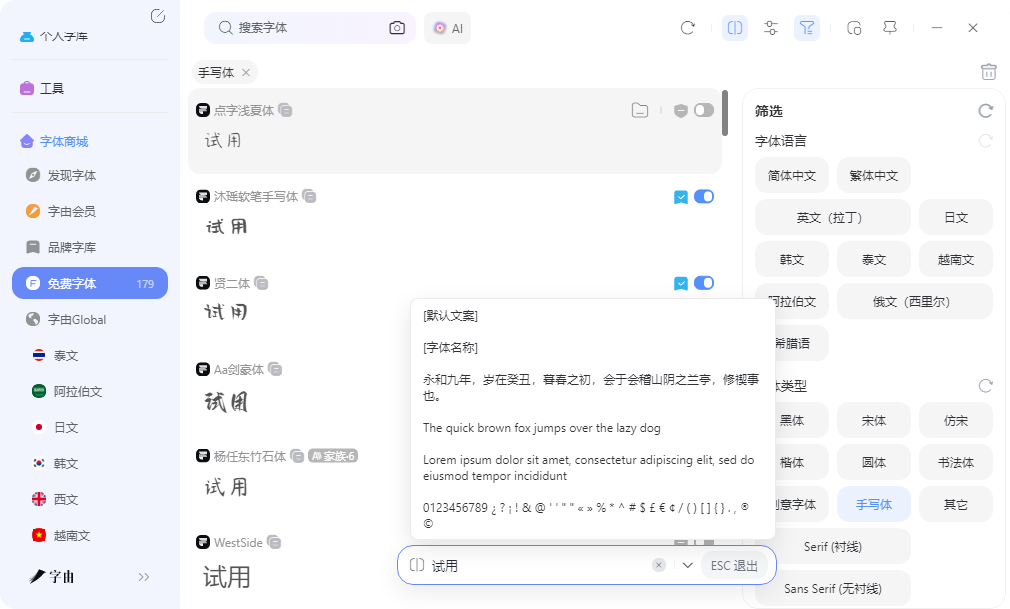
生成自己的手写字体,把你的笔迹变成电脑字体
把自己的笔迹变成电脑里能用的字体,或者在文档里打出一段像手写的文字,这两种需求都有对应的在线工具可以解决。有的工具通过上传手写稿照片生成字体文件,有的把普通文字渲染成手写风格图片。这篇文章测试了5款工具,操作难度和输出格式不同,总有一款适合你。
字由的字体库中设有手写体分类。用户打开字由客户端后,找到筛选栏的字体类型中勾选手写体,系统会列出所有手写风格的字体。这些字体包括演示悠然小楷、点字手写漆书、字由芳华体等,总计数十款。每款字体都标注了免费商用标签,用户可以放心用于商业项目。
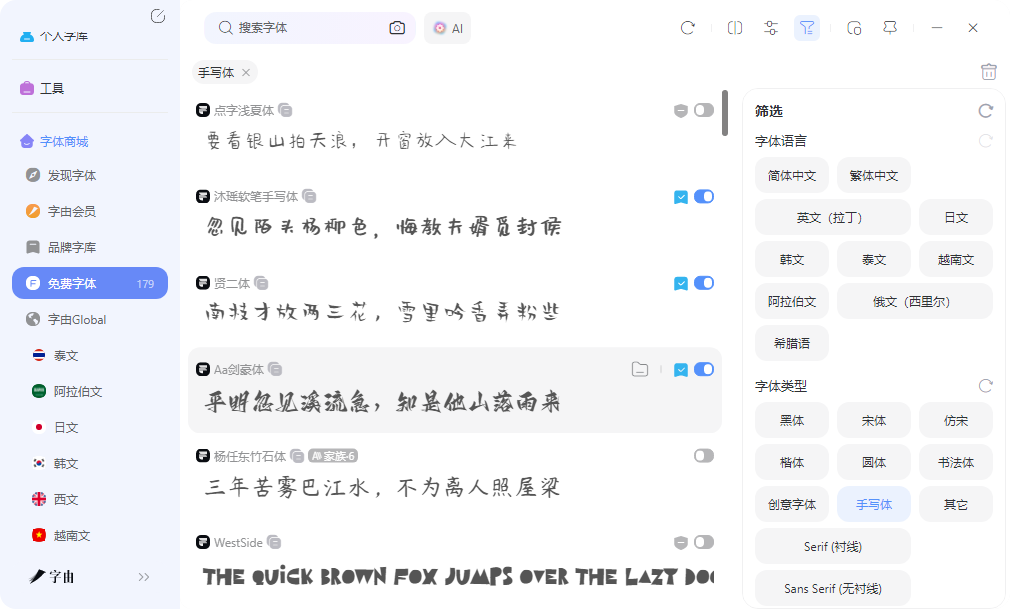
筛选手写体后,用户可以在预览区输入自己的文案,例如一段签名或一句 slogan,页面会实时显示该字体应用到文案上的效果。这个预览功能不需要激活字体,用户可以先对比多款手写体的笔画特征和整体气质。
2、handtext
第二个工具是handtext。它主要将用户输入的文本转换成看起来像手写的页面,适合生成手写版作业、笔记或信件。用户可以在编辑器中粘贴或打字输入文字,也可以上传PDF文件。页面右侧提供了多种设置选项,包括纸张类型(如A4)、方向(纵向或横向)、字体选择(支持多种手写字体)。设置完成后点击Generate按钮,系统生成手写风格的输出。输出结果可以直接打印,也可以导出为PDF。
该工具的操作界面简洁,不需要注册即可使用。生成的页面看起来像是用笔在纸上写出来的,包括字迹的深浅变化和不规则的排列。对于需要提交手写版作业的学生,或想给信件增加手写效果的用户,这个工具可以节省大量时间。免费版可能有字数限制,日常使用足够。
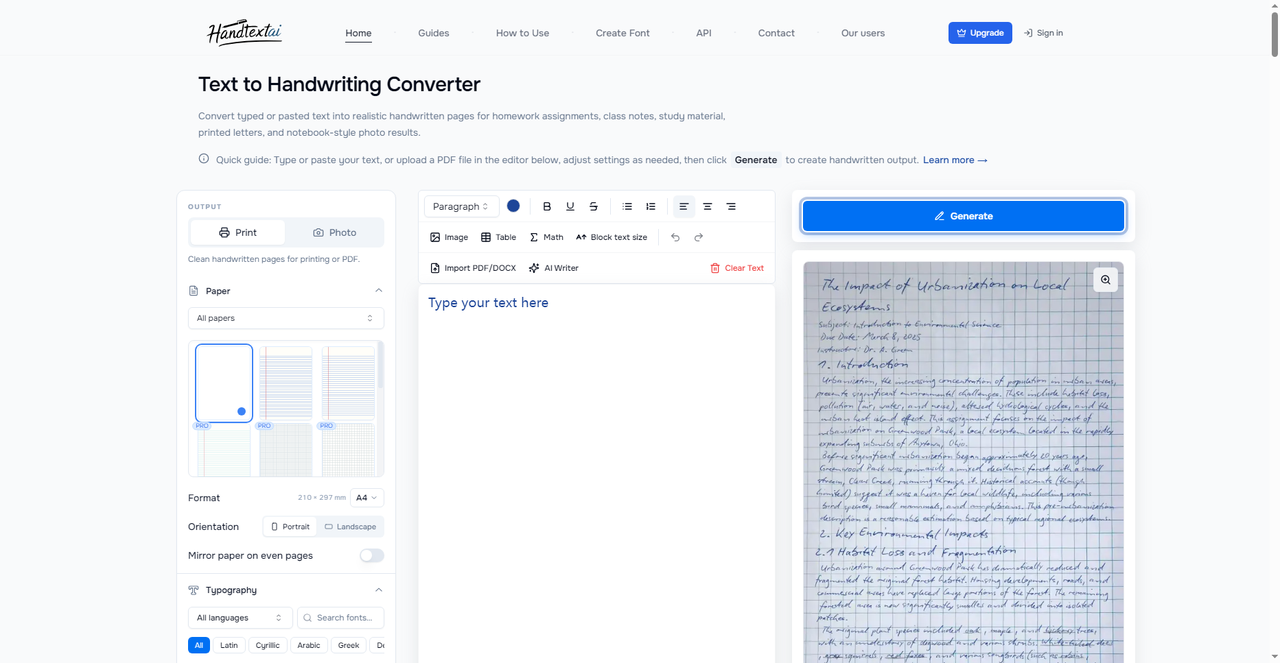
3、ScribbleSync
第三个工具是ScribbleSync。它与大多数手写生成器不同,不要求用户打印模板再扫描。用户直接在手机、平板或电脑屏幕上逐字绘制自己的笔迹,保存每个字母、数字、标点符号以及常见字母组合(如th、in、is、ll、ing等)。绘制完成后,用户输入任意文字,系统会调用保存的笔迹数据,生成整段手写效果。
ScribbleSync的核心优势是保留了真实的笔迹连贯性。大多数手写字体生成器把每个字母作为独立单元组合,导致单词中的字母之间缺乏自然连笔。ScribbleSync支持保存常见字母组合,生成的文字更接近真实的书写习惯。用户可以将生成结果导出为PNG图片、透明背景PNG或PDF文件。该工具适合需要长期使用同一套笔迹的用户,例如制作个性化日志、手写体设计作品集。
4、Handwriting Font Generator
第四个网站是Handwriting Font Generator。用户在上方输入框中输入文字,下方展示多种手写风格的结果,包括Cursive(草书)、Neat Handwriting(整洁手写)、Elegant Script(优雅花体)、Fancy Signature(花式签名)等。每种风格以预览图形式展示,用户可以复制样式文本或下载图片。
该工具的操作最直接:输入文字,点击生成,立刻看到效果。不需要调节参数,不需要逐字绘制,也不需要上传参考图。生成的手写效果适合用于社交媒体配图、个人博客题图、电子邀请函等场景。完全免费,无需注册。输出图片的分辨率适合网页使用,印刷可能需要更高清晰度的工具。
5、在线手写文字生成工具
第五个工具是一个在线手写文字生成页面。用户输入文本后,可以从字体下拉菜单中选择多种手写字体(如Arizona-Regular),调节字体大小(默认24px)、文字颜色、外边距(20px)、行间距(16px),还可以添加下划线(实线)、设置线条宽度和颜色。设置完成后点击生成按钮,系统输出手写效果图片,用户可以下载保存。
该工具的优点是参数可调范围大。如果用户对默认的手写效果不满意,可以微调字号和行间距,找到最舒适的阅读效果。下划线功能适合生成仿手写批注或重点标记。页面提示不同字体支持的文字范围不同,有的只支持中文,有的只支持英文,使用前需要确认。完全免费,首次加载字体可能需要等待10到60秒。
把普通文字变成手写效果,关键看你要做什么用。如果需要一款能反复打字的手写体,字由的字体库里就有几十款现成的免费手写字体,激活后直接装在PS和Word里,想打什么字就打什么字,不用每次重新生成。handtext适合生成整页手写笔记或作业,ScribbleSync能保存你自己的真实笔迹重复使用,Handwriting Font Generator把短文本转成手写预览图,在线手写生成工具可以调节字体大小和行间距。如果是日常做海报、做简历、做包装需要手写体,字由是最省事的方案——挑一款顺眼的,点一下激活,后面全在软件里打字搞定。其他几个工具应付特定场景够用了,但论顺手和长期使用,字由排第一个。